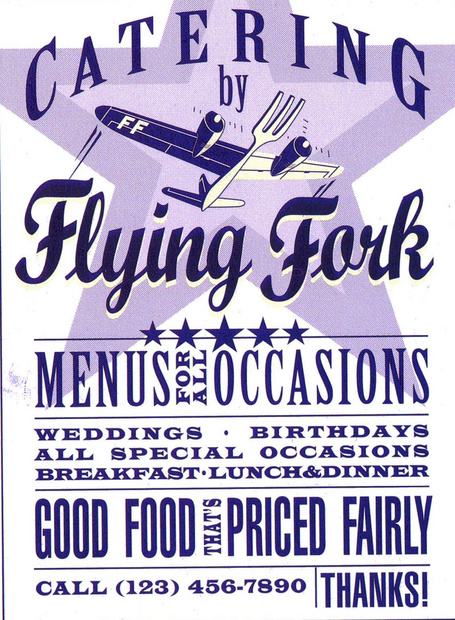
Schriftart von "Flying Fork" aus Buch 'layout index'
suche schon seit Tagen vergeblich nach der Schriftart in dem Buch 'layout index' die beim Beispiel des Catering-Service "Flying Fork" verwendet wird.
Bräuchte diese oder auch gerne alternative Schriftarten für einen Logo-Entwurf der nostalgisch wirken soll. Also die "gute alte Zeit" verkörpern soll.
Über alternative Schrift-Vorschläge würde ich mich freuen!